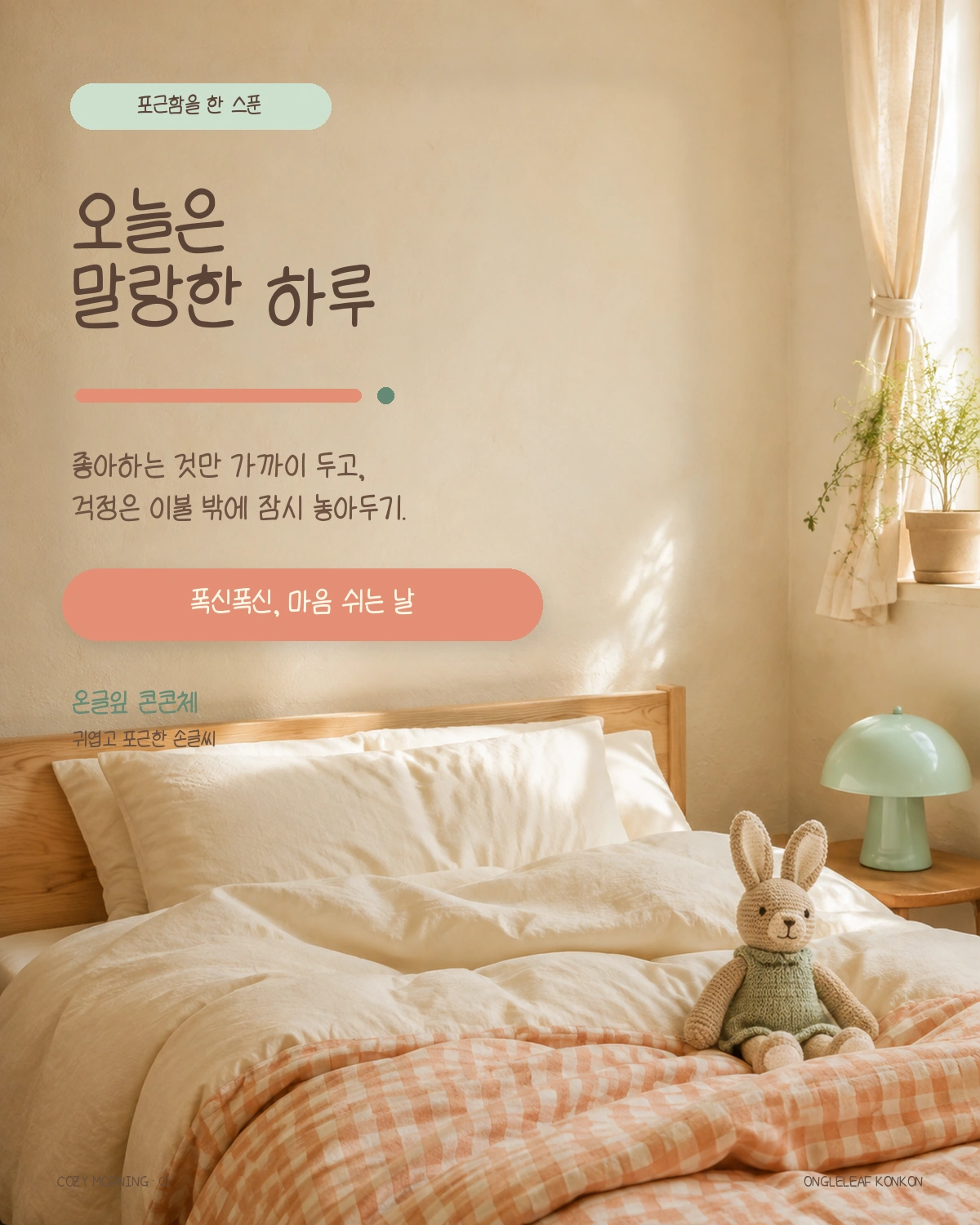
온글잎 콘콘체 — 온글잎에서 배포하는 무료 폰트입니다. 동글동글한 획으로 포근하게 눌러쓴 서체로, 카드뉴스와 영상 자막에 두루 어울리는 손글씨체
온글잎에서 2022년에 나온 손글씨 서체입니다. 로마자 이름이 corncorn이라 콘이 옥수수를 뜻하는 것으로 보이지만 제작사 설명이 없어 단정할 수는 없습니다. 글씨 주인도 이니셜만 공개돼 있습니다.
디자이너의 한마디라고 붙은 문장은 온글잎이 제공한 기본 문구라 조형과는 관계가 없습니다. 그래서 형태는 파일을 보고 적습니다. 온글잎 여섯 종 가운데 유일하게 받침 유무에 따른 높이 차가 거의 없는 네모틀이라 글줄이 가지런하고, 획이 굵어 자면을 채우는 비율도 여섯 종 중 가장 높습니다. 손글씨인데도 정돈된 인상을 내는 이유가 여기 있습니다.